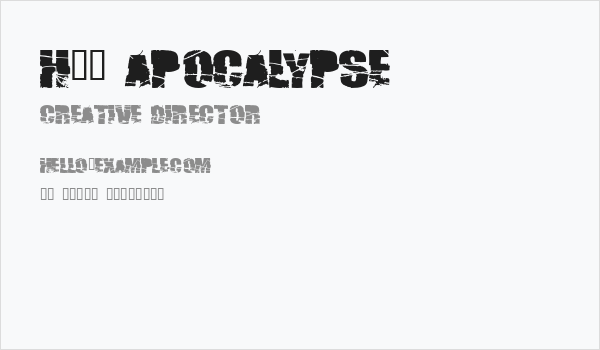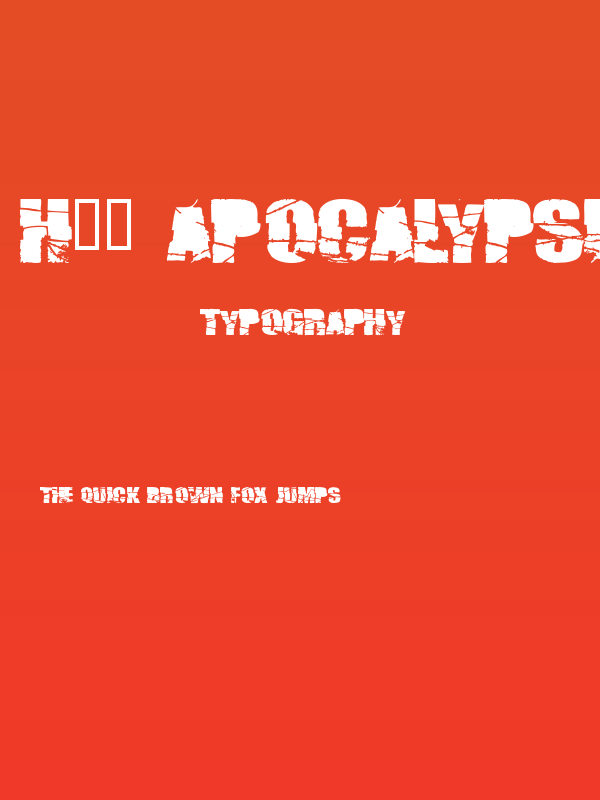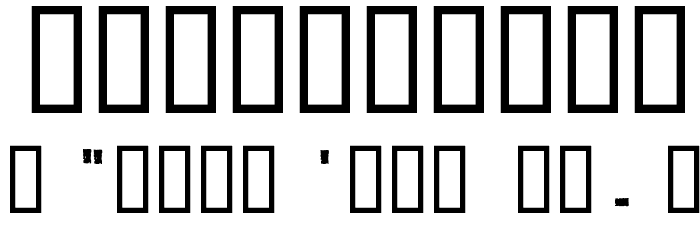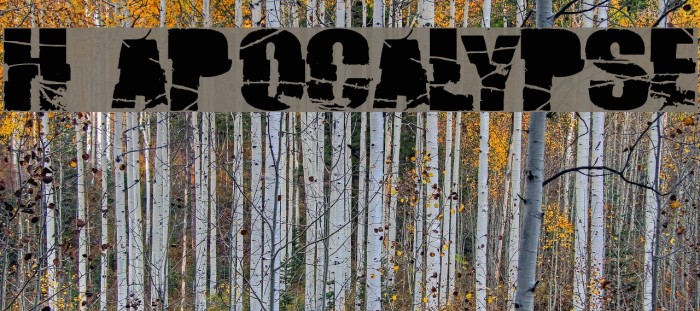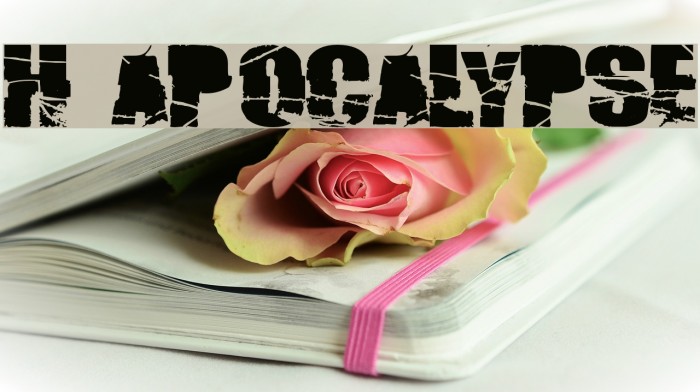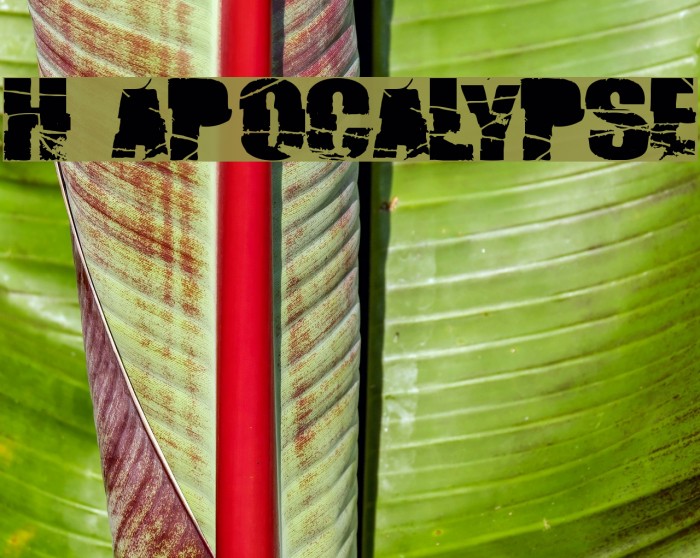
H74 Apocalypse Font
✎ Distorted Eroded
| Proiecte propuse | Ideal for use in posters, album covers, video game titles, and any design that requires a gritty, impactful look. |
| Autor | Fonts by Måns Grebäck |